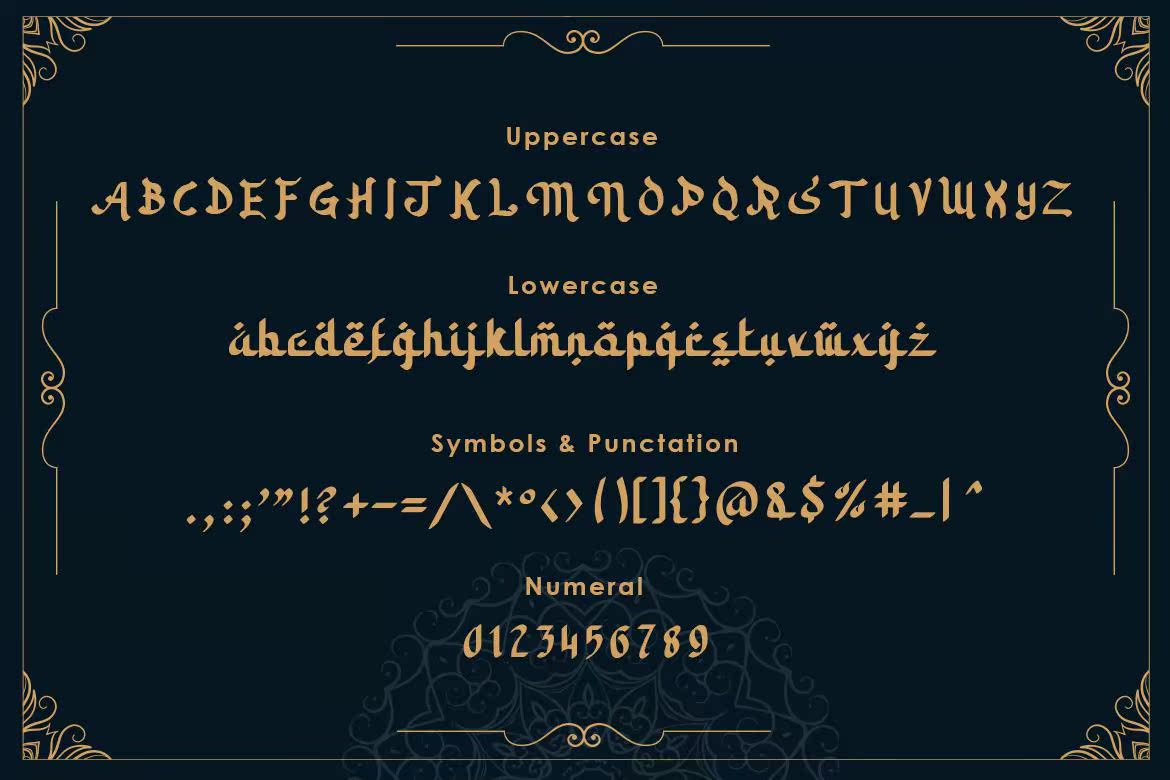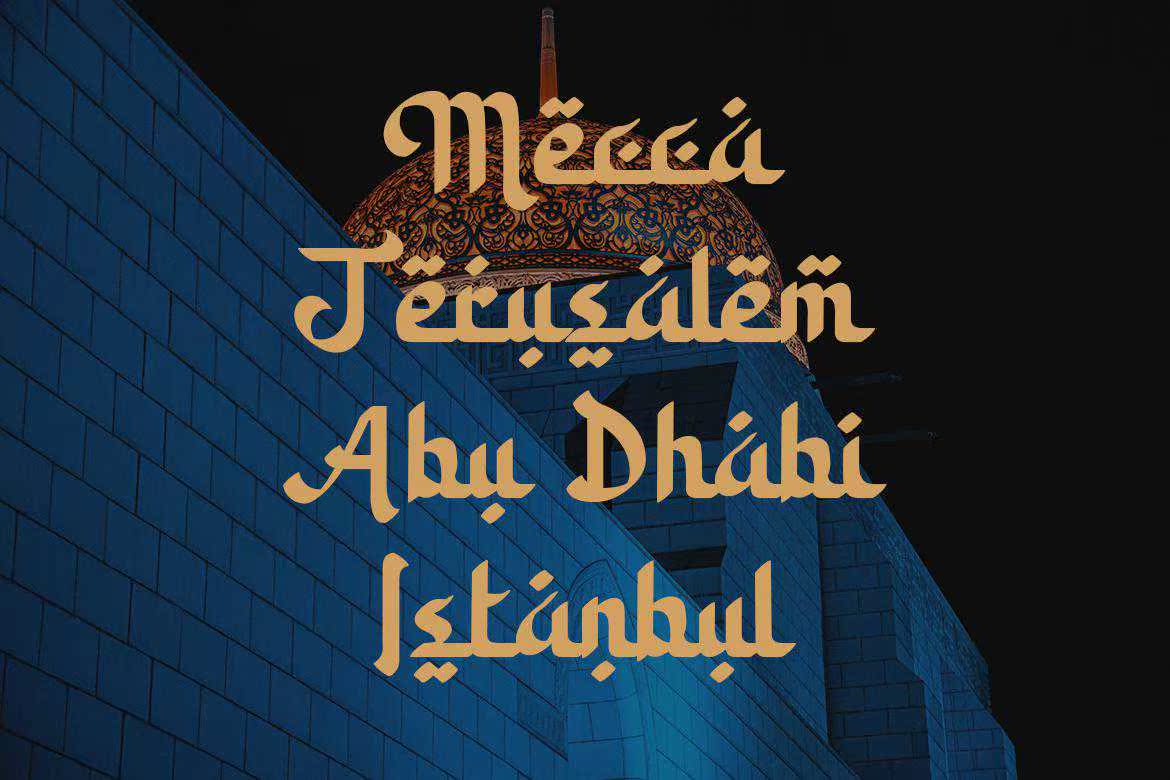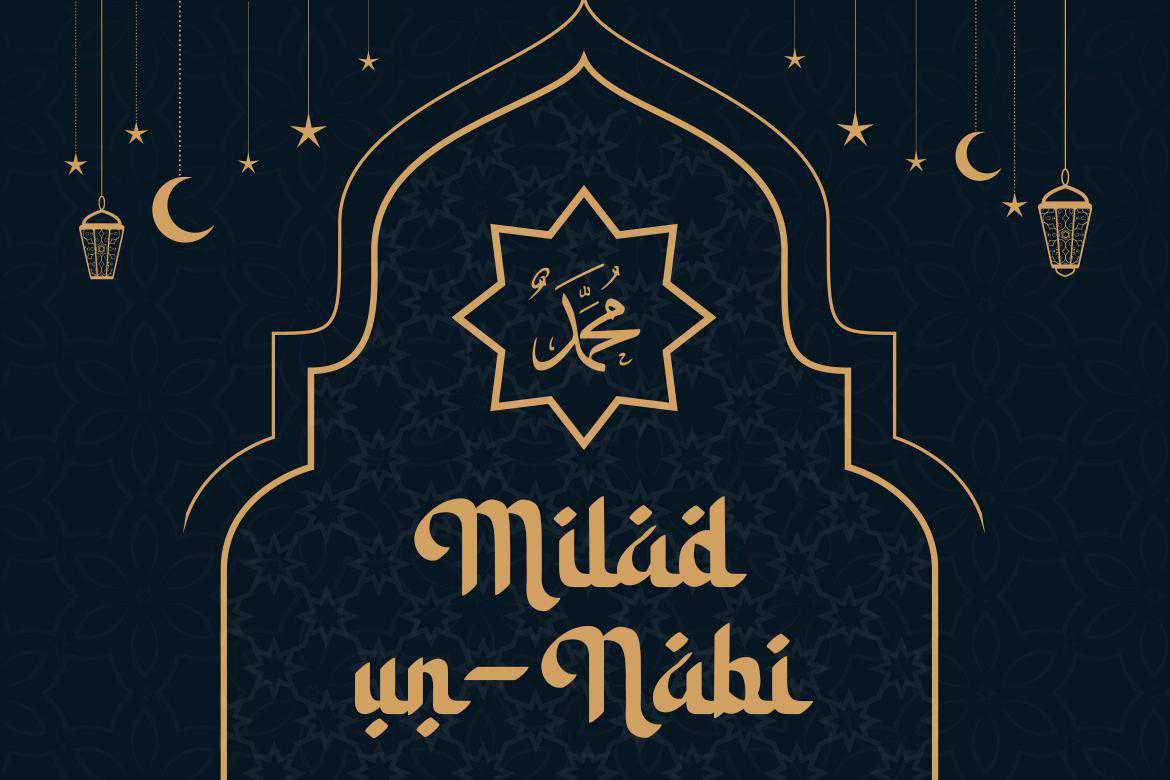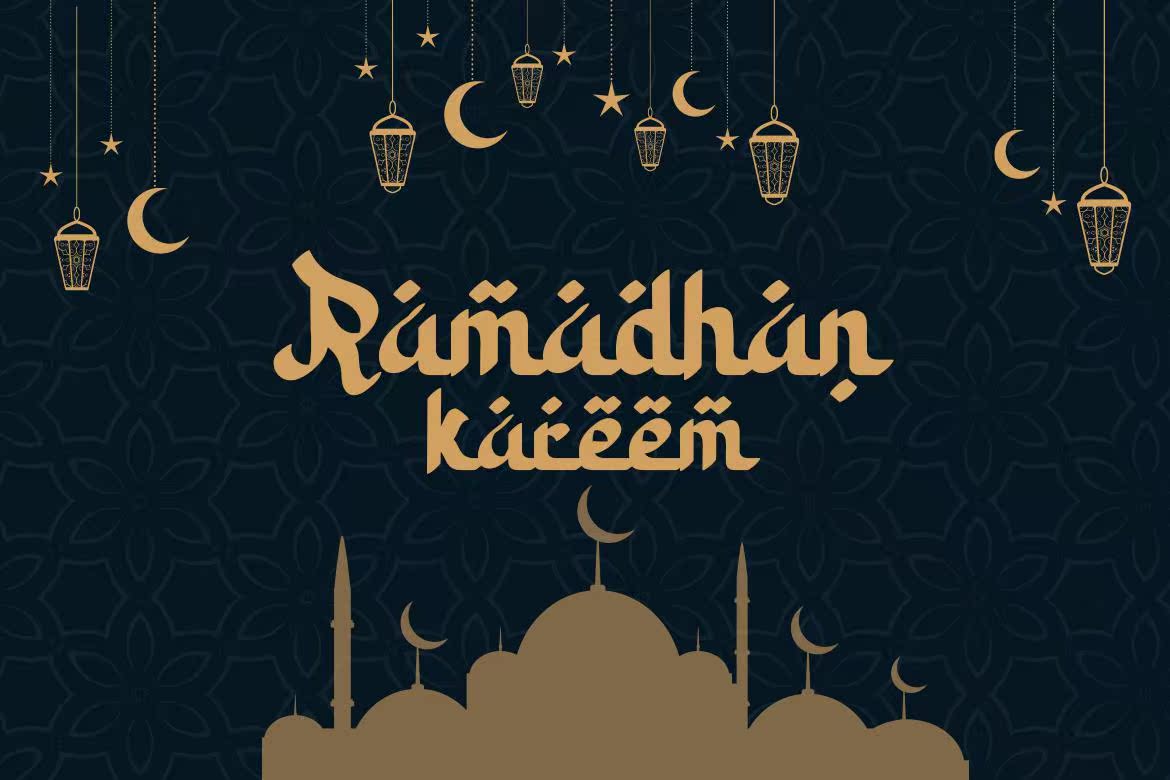
Kahlilisan Arabic内容是由中东感觉的Mee设计的,但对他们的现代设计来说不够简单。内容包括风格设置和它的创造性标题,在Web和打印上,对于CrollText来说是完美的。Well Balanced Letters可供阅读的区块或标题。完整版本下载此处:Kahlilisan Arabic内容是由中东感觉的Mee设计的,但对他们的现代设计来说,没有足够的简单。内容包括风格设置和在Web和打印上的创造性标题,非常适合于CrollText。平衡字母适合于可阅读的文本块或标题。完整版本下载此处: